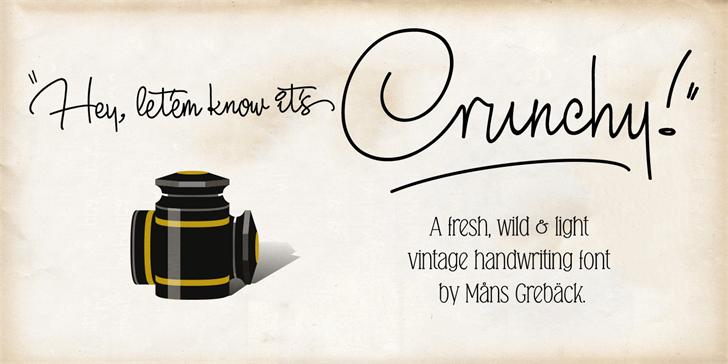
A fonte Crunchy é criada pelo designer Hamilton e oferece uma escrita handwritten envolvente que se destaca por sua delicadeza e naturalidade. Se você está procurando uma fonte para projetos gráficos que não pareça forçado ou estilizado, a Crunchy pode ser seu parceiro perfeito. Com seus traços suaves e linhas leves que lembram um desenho feito à mão, essa fonte oferece uma textura única que se adapta bem tanto para títulos quanto para texto de corpo em projetos impressos ou digitais. Se você está em busca de algo além do estereotipado, a Crunchy é uma excelente escolha para trazer um toque único e personalizado à sua identidade visual. Visite o site oficial de Hamilton para mais detalhes sobre comprando uma licença comercial.